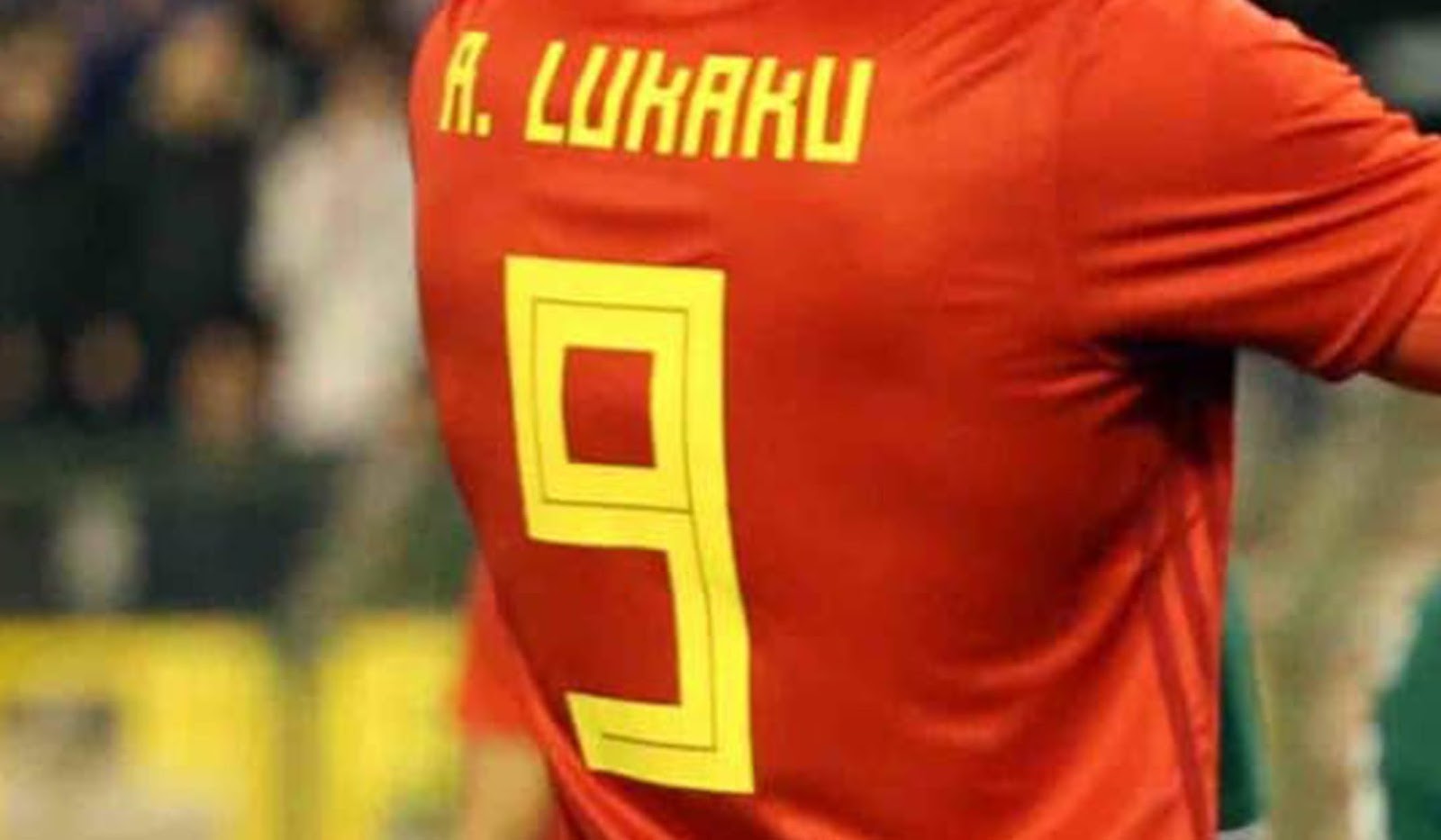
Mexiko debütiert "schlechte" Adidas WM 2018 Schriftart
Mexiko hat ihr brandneues WM 2018 Heimtrikot am Freitag gegen Belgien debütiert. Während das Mexiko WM 2018 Trikot goldrichtig und genauso wie erwartet war, war die Schriftart von Mexiko im Spiel nicht so, wie Adidas es gewollt hatte.
Mexiko verwendet unveränderte + schlecht erstellte WM 2018 Schriftart
Mexikos Nummern fehlte das Mexiko-Wappen als auch die Linien innerhalb der Schriftart (via @unniquadium‏).
Mexikos Schriftart im Spiel gegen Belgien fehlte es an zwei wichtigen Teilen. Erstens hatte Mexikos Schriftart nicht das Wappen des Verbands am unteren Ende. Zweitens fehlte den Nummern die Linien innerhalb der Nummern.
Während Mexikos Schriftart vollkommen schlicht war, war auch Belgiens Schriftart nicht perfekt vorbereitet, weil den Nummern die Silhouette des belgischen Verbands am unteren Ende fehlte.
Argentinien & Deutschland haben es richtig gemacht